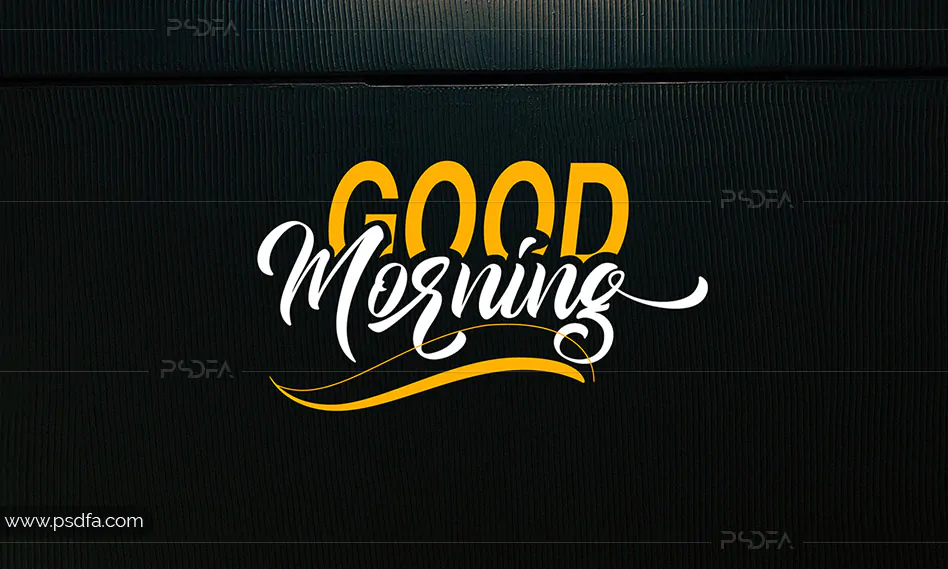
اسکریپت فونت انگلیسی فوقالعاده زیبای Good Morning
اسکریپت فونت انگلیسی Good Morning
اسکریپت فونت انگلیسی Good Morning که در این مطلب شاهد آن هستید یکی دیگر از سری فونتهای فوقالعاده زیبای انگلیسی است که میتوان از آن در طرحهای گرافیکی به خصوص طراحی انواع پوستر استفاده نمود. این فونت در قالب 2 فایل otf, ttf بر روی سایت بارگذاری شده است که با نصب یکی از این دو فایل در پوشه فونتهای سیستم قادر به استفاده از آن در تمام نرمافزارهای گرافیکی و ویرایشگر متن از جمله نرمافزار فتوشاپ، افترافکت، ورد، پاورپوینت و … خواهید بود. فونت Good Morning در وزن معمولی (Regular) ایجاد شده است که میتوانید آن را در طراحی انواع کارت تبریک، کارت پستال، بروشور، کارت ویزیت، بنر، پوستر، تراکت و سایر طرحهای گرافیکی مورد استفاده قرار دهید.